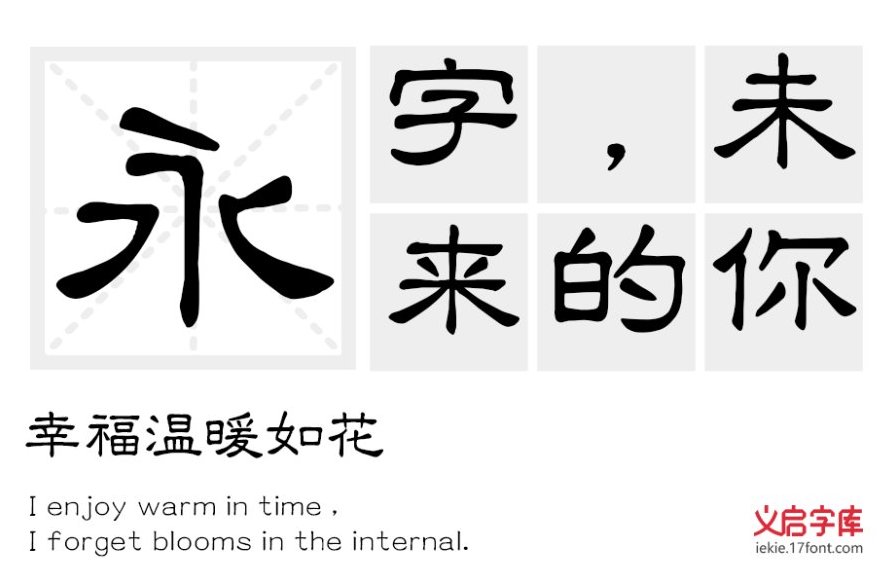
中国书法在历史的长河里不断沉淀,与汉文化的存在有着密不可分的关系,那么书法究竟有哪几种,大家知道吗?小编放出的这张 字体图片 大家能看出是哪一种书法形式吗?
所谓书法字体,也就是书法风格的分类。传统来讲,我国书法字体大致分为篆书、隶书、草书、行书和楷书这五大类。不过在每一大类里面又分为若干细小门类,比如篆书分为大篆和小篆,楷书又有魏碑唐楷之分,还有二王体、瘦金体等之说。
隶书,亦称汉隶,是汉字中常见的一种庄重的字体,书写效果略微宽扁,横画长而直画短,呈长方形状,讲究蚕头雁尾、一波三折;隶书起源于秦朝,由程邈形理而成,在东汉时期达到顶峰,书法界有汉隶唐楷之称。
图片识别字体 为“义启隶书体”,这款字体笔画上保留深化了波折的元素,由于考虑到整体的可塑性,起收处弱化方笔加强圆笔画,所谓蚕头雁尾修饰弱化些。结构内放外收,整体呈扁方形,重心在一条轴线上。章法,左右波折遥相呼应,气息通畅一气呵成。